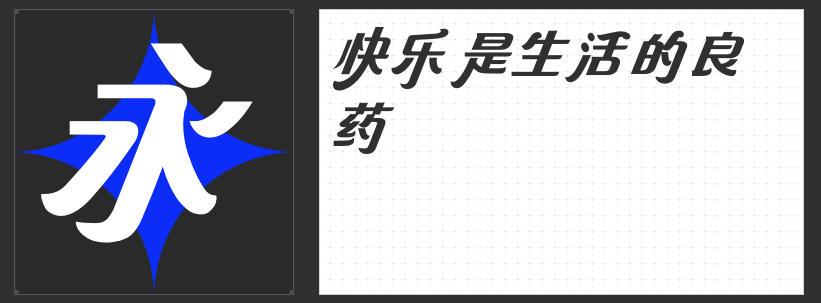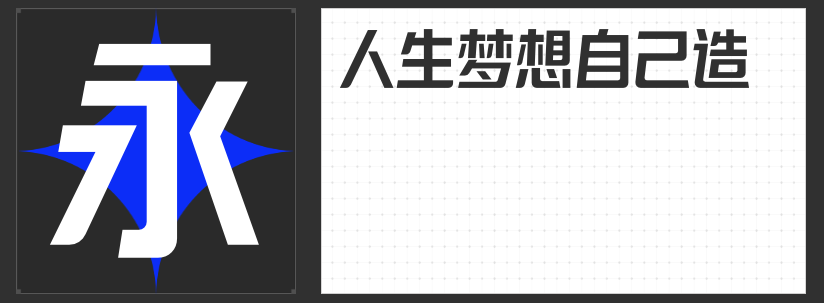
标题设计的视觉革命:四款高张力字体的美学突围
在信息爆炸的视觉场域中,标题字体是品牌与受众对话的第一声呐喊。以下四款原创字体以突破性的设计语言重构标题美学,从传统笔法的解构到几何形态的重组,为设计注入兼具冲击力与艺术性的视觉能量。
一、造字侠伏魔简繁 传神
这款字体以“力透纸背”的书写哲学为核心,通过强化笔画粗细对比与动态收放,构建出极具戏剧张力的视觉框架。其“勾、提、挑、捺”等笔画被夸张处理——捺画如刀锋劈裂空间,勾画似铁钩锁住视线,在保持汉字结构中正性的同时,通过笔画的延展与顿挫形成内在韵律。单字内部空间疏密有致,收放自如的布局使标题排版兼具呼吸感与压迫性,尤其适合需要传递权威感或仪式感的设计语境。
二、造字侠郝刚快乐简 微黑
将西文斜体的浪漫基因注入汉字隶书的骨骼,这款字体以112度倾斜角度打破静态平衡。其创新在于通过撇捺笔画的错落变化模拟蚕头燕尾的书写节奏,同时以微妙的字重变化构建视觉韵律——横画纤细如琴弦,竖画厚重如琴柱,在倾斜的动态中形成自洽的节奏体系。这种中西合璧的设计语言,为时尚、文化类标题提供了兼具国际感与传统韵味的解决方案。
三、励字铁拳简 超级黑
以“铁拳出击”为概念,这款创意黑体通过极致的笔画粗化与字面扩张,将书写痕迹转化为几何块面的力量符号。其折角采用圆润处理,在刚硬中注入一丝柔韧,饱满的笔画如肌肉线条般充满张力。这种“重剑无锋”的设计哲学,使字体在远距离阅读时依然保持高辨识度,尤其适合运动、科技等需要传递爆发力与现代感的标题场景。
四、励字造梦简 大粗
灵感源自“青春筑梦”的抽象表达,这款字体以不对称结构模拟建筑的透视关系——左侧倾斜15度制造动态失衡,右侧竖直保持视觉锚点,在矛盾中构建空间张力。其棱角分明的直线与夸张的透视感,如同仰视摩天大楼时的视觉体验,将文字转化为具有纵深感的视觉雕塑。这种突破传统的设计逻辑,为城市文化、未来科技等主题的标题设计提供了充满想象力的解决方案。
这四款字体通过笔法解构、结构创新与美学融合,重新定义了标题字体的设计边界——从笔墨浓淡到几何透视,从文化转译到力量爆发,为设计师提供了跨越传统与现代的多元表达工具。